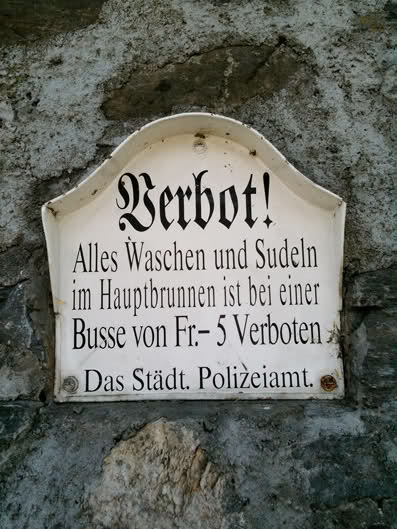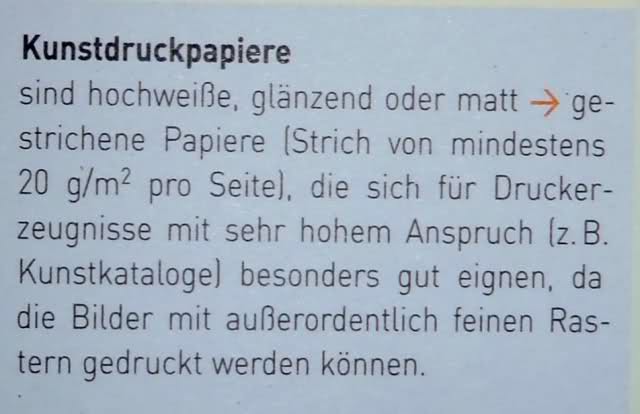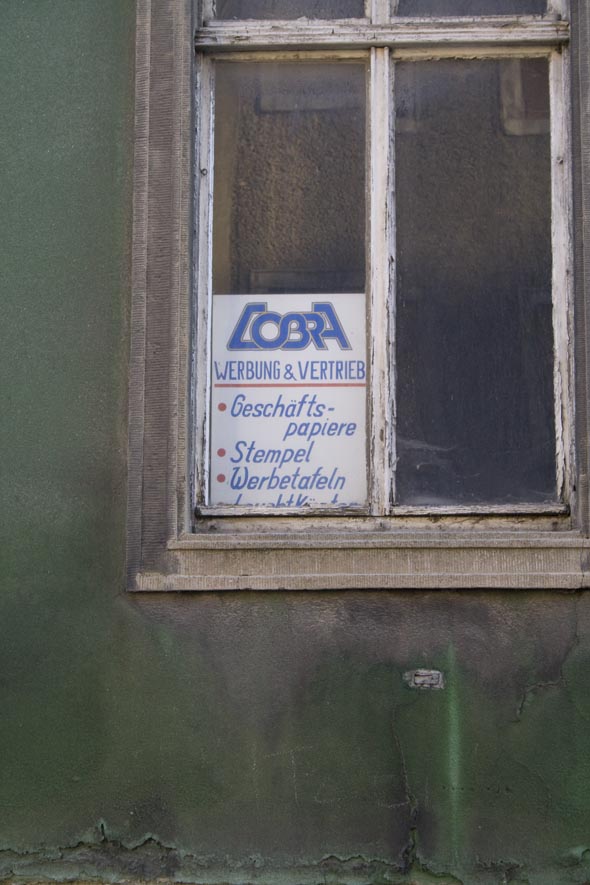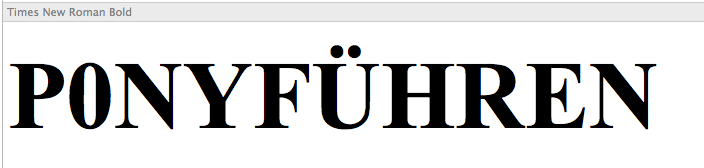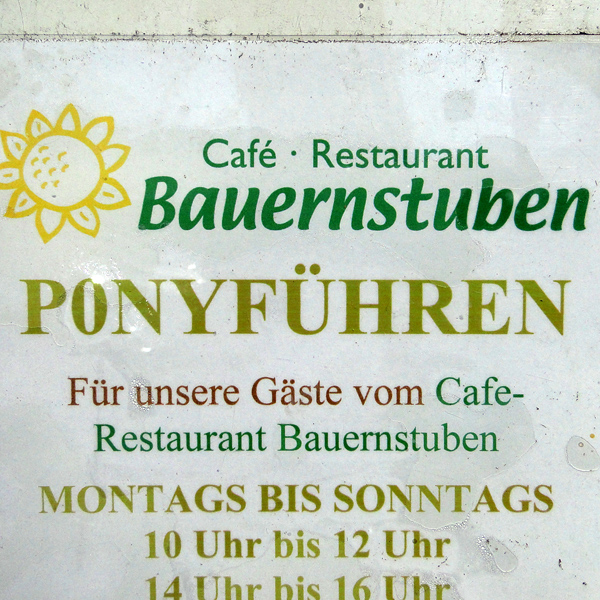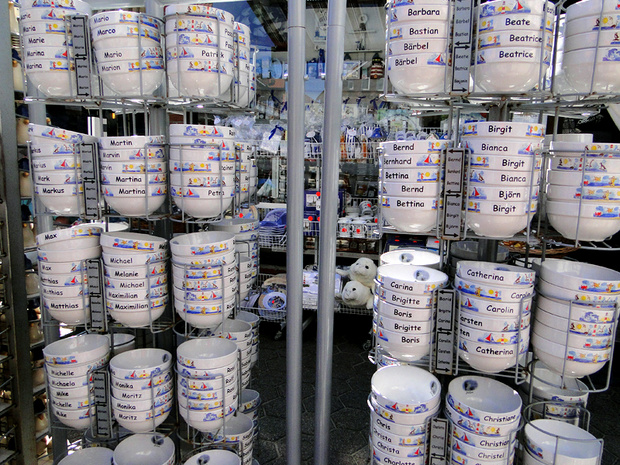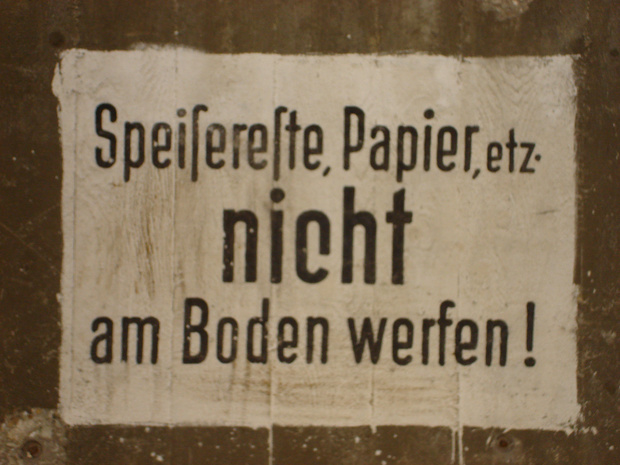
Weil diese Trennung wirklich schön ist und damit ihr in Zukunft auch alle eure Drucker-Zeugnisse immer auf Kunstdruckpapier druckt …
Aus dem wie ich finde sehr guten handinhandbuch das kleine einmaleins der druckvorstufe.
Die Höhe der Buße richtet sich nach dem Grad der Alleswaschung und der Sudlungsdichte. Sie ist variabel. Und es ist sehr verboten! Weil … ja, das ist dann im Fall ein großes Verbot! Und es gibt keine Nebenbrunnen. Und die Tafel hat ein Dächli. Gegen Waschungen und Besudelungen von scharf scheißenden Vögeln.
Grüsse ohne Eszett : )
jepp, comic sans. bin richtig erschrocken als ich die ganzen tassen sah.
aber wer sowas kauft hat es nicht anders verdient ;)
das ist keine 0 das ist das condensed O der times, gibts nur auf extra anfrage bei microsoft. ;)
… condensed O der times …
Das kannst du gar nicht beurteilen, du kennst ja nur Kleinbuchstaben :baeh:
PNullyführen stimmt schon :-)
Aufschrift in einem als Schutzraum verwendeten Stockwerk in einem der wiener Flaktürme
Es ist die einzige, die ein ſ aufweist.